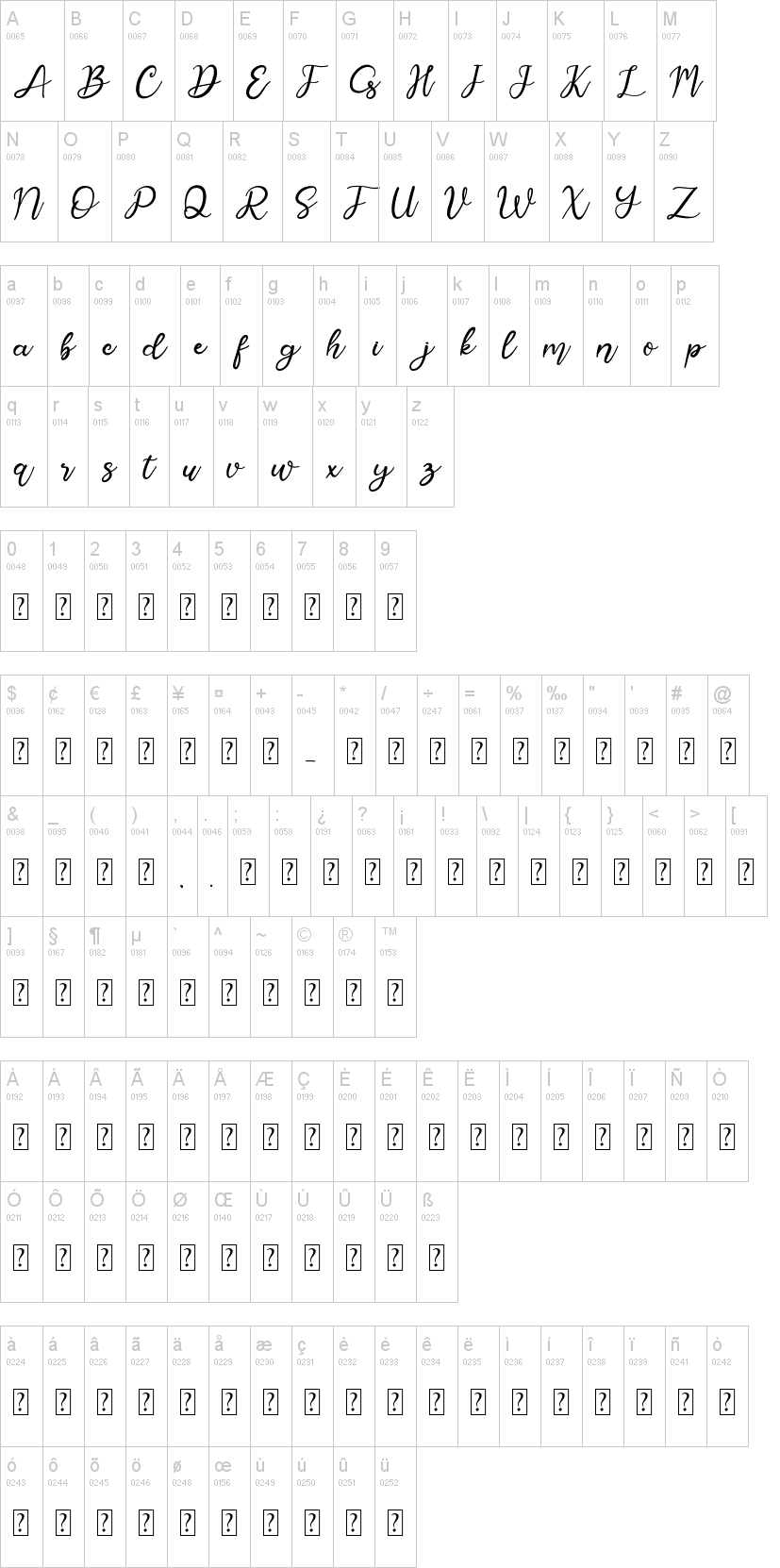
Aylogri字体是一款简洁、优雅、易读的英文字体,它由两个字体组成:Aylogri Regular 和 Aylogri Bold。Aylogri Regular字体采用细节精致的线条,使字体看起来更加精致,而Aylogri Bold字体则拥有较高的粗细度,能够更好地表达字体的强烈感觉。Aylogri字体具有良好的可读性,并且拥有非常优越的空间效率,可以在较小的空间内显示出更多的文本。内容介绍
Aylogri是一款非常不错的手写艺术字体,具有很好的视觉感,适合于文化类的宣传设计、商业类品牌的广告和产品包装设计以及个性化文字排版等较多场景。